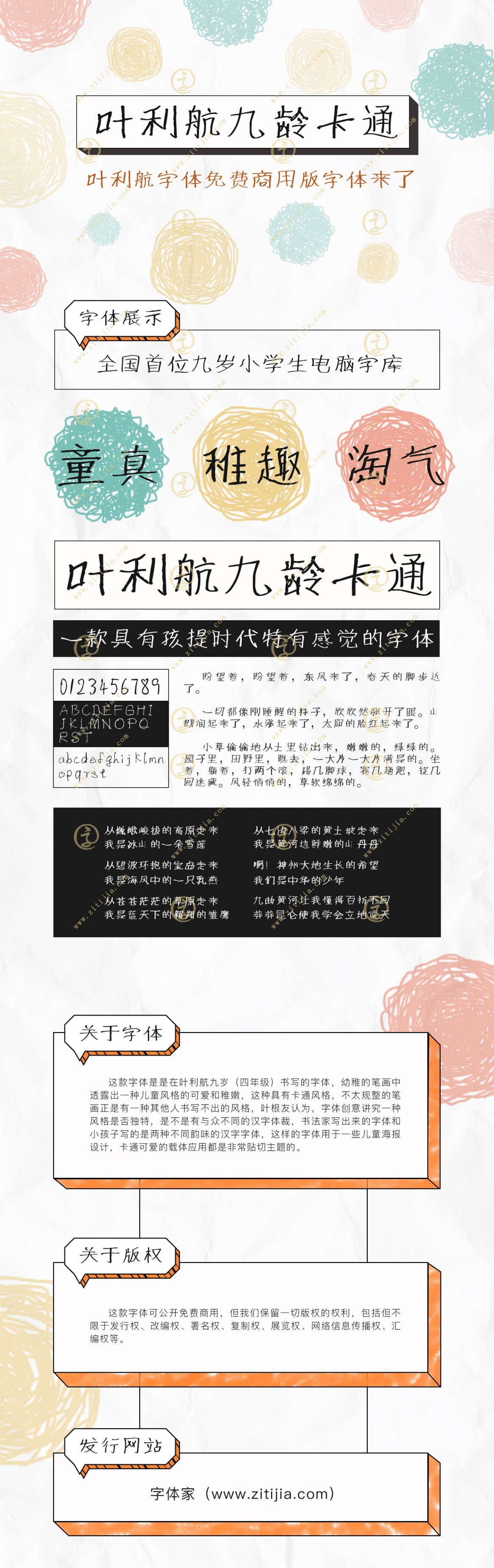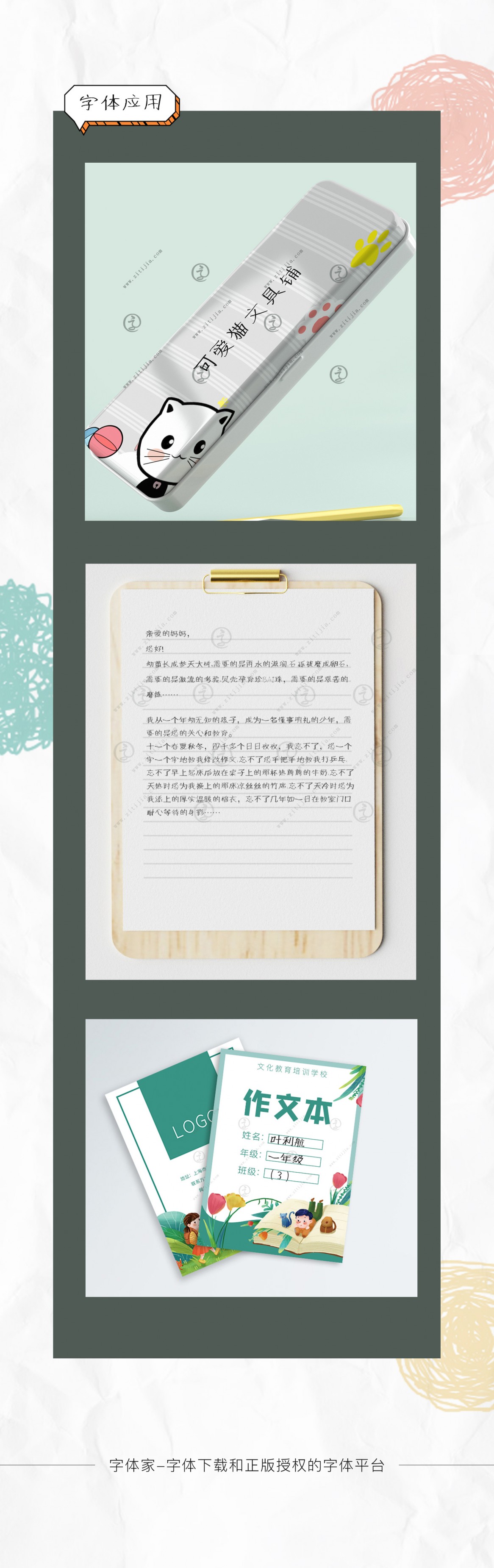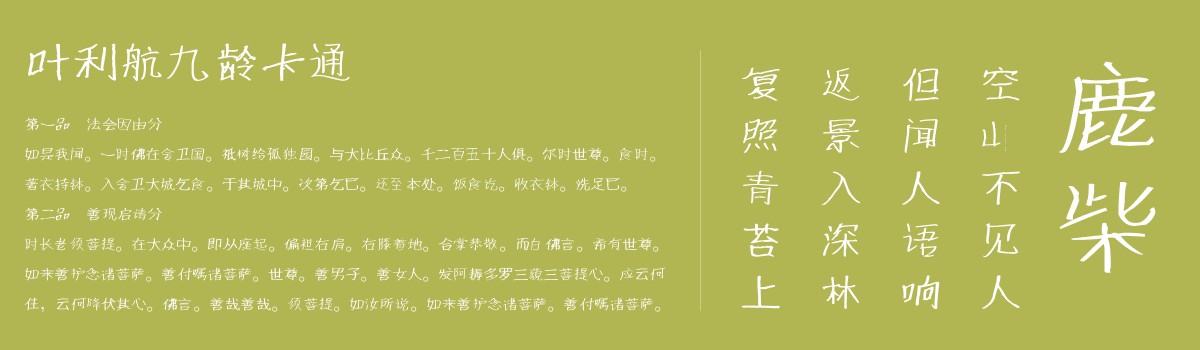
叶利航字体免费商用版字体来了!!
关于字体:
这款字体是在叶利航九岁(四年级)书写的字体,幼稚的笔画中透露出一种儿童风格的可爱和稚嫩,这种具有卡通风格,不太规整的笔画正是有一种其他人书写不出的风格,叶根友认为,字体创意讲究一种风格是否独特,是不是有与众不同的汉字体裁,书法家写出来的字体和小孩子写的是两种不同韵味的汉字字体,这样的字体用于一些儿童海报设计,卡通可爱的载体应用都是非常贴切主题的。